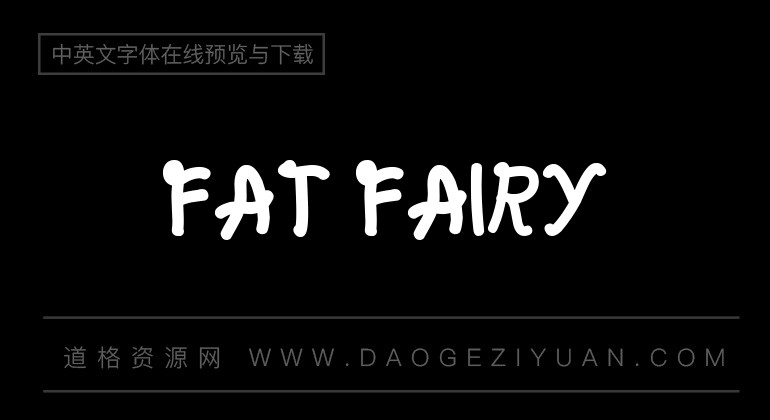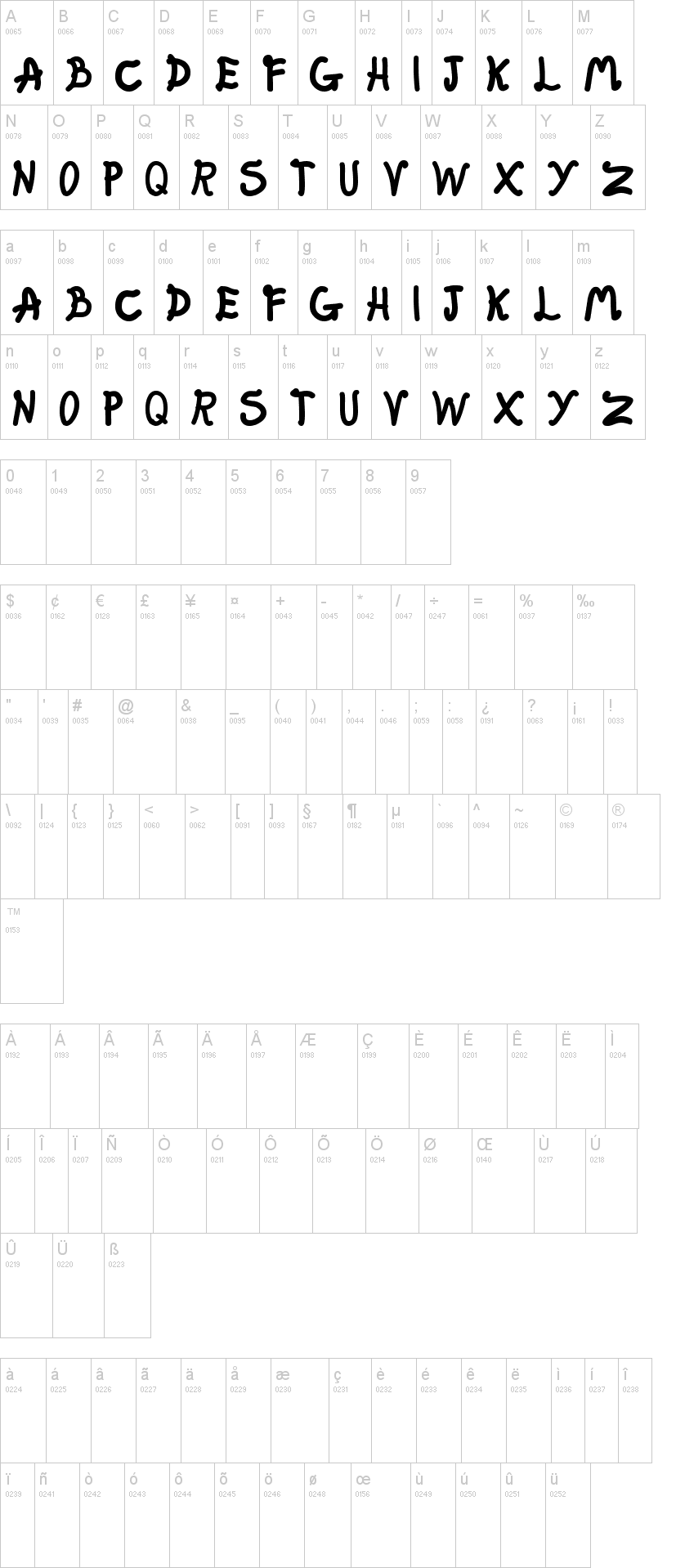
? Fat Fairy 字体是一款拥有可爱又活泼的风格的英文字体,它具有温暖的曲线,非常适合用于儿童类的文本内容,也可以用于小清新类型的设计中。它具有特殊的设计,拥有更多的可爱的细节,可以为设计师带来更多的创意灵感。内容介绍
Fat Fairy是一款非常不错的手写艺术字体,具有很好的视觉感,适合于文化类的宣传设计、商业类品牌的广告和产品包装设计以及个性化文字排版等较多场景。